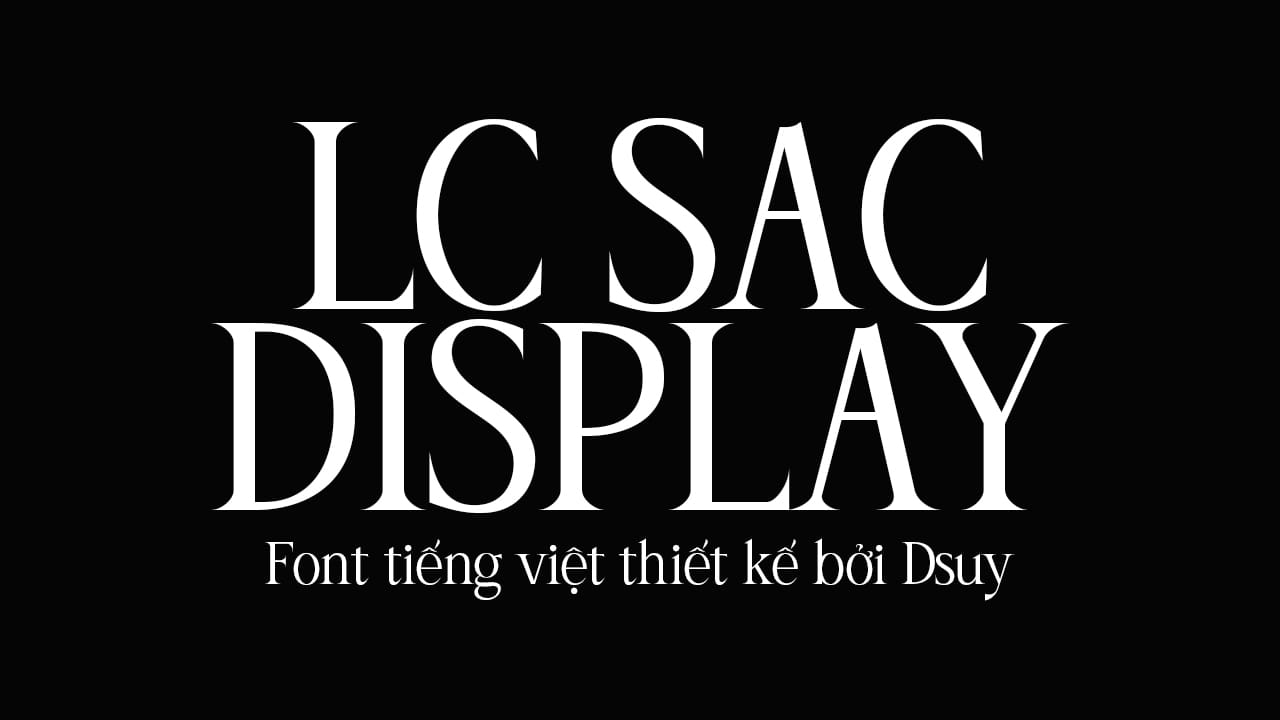
Trong tiếng Việt, Sắc có nghĩa là sắc đẹp, sắc sảo.
LC Sac Display được lấy cảm hứng mạnh mẽ từ chữ cái La Mã vào thế kỷ thứ 4 với serif rất sắc nét. Trong suốt quá trình thiết kế, một số chi tiết hiện đại được phát triển một cách tỉ mỉ để tôn lên đặc tính của nó.